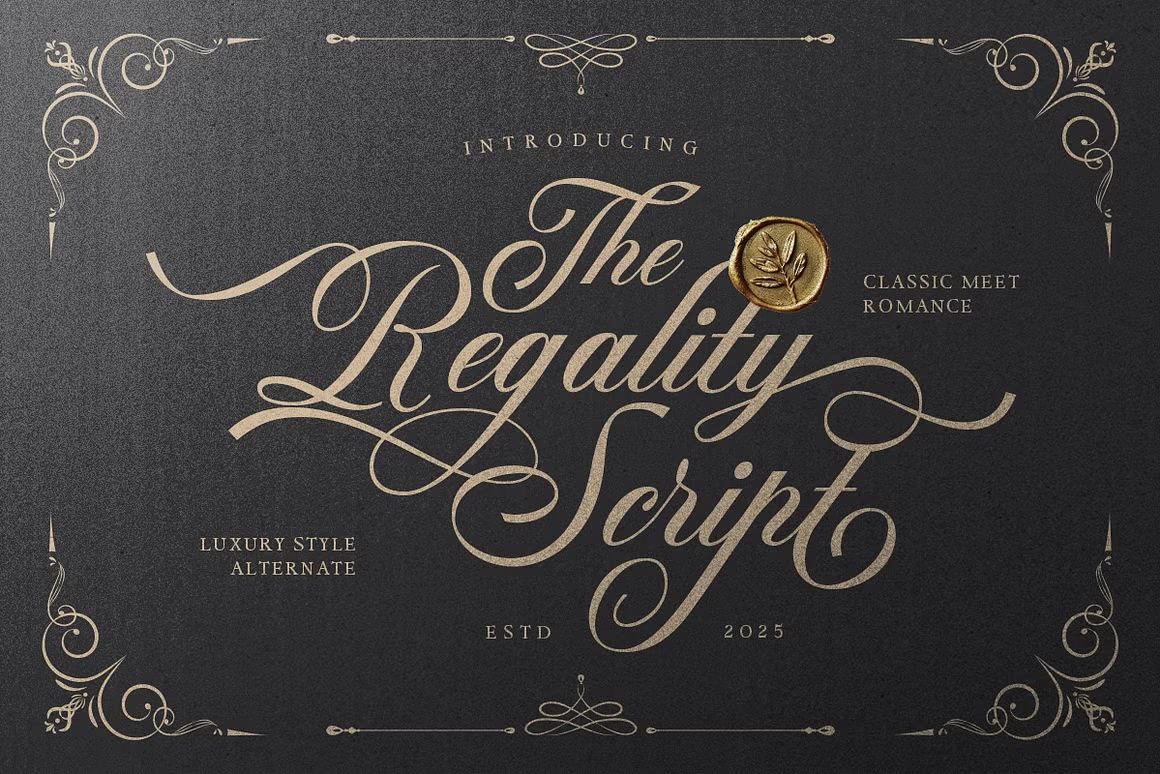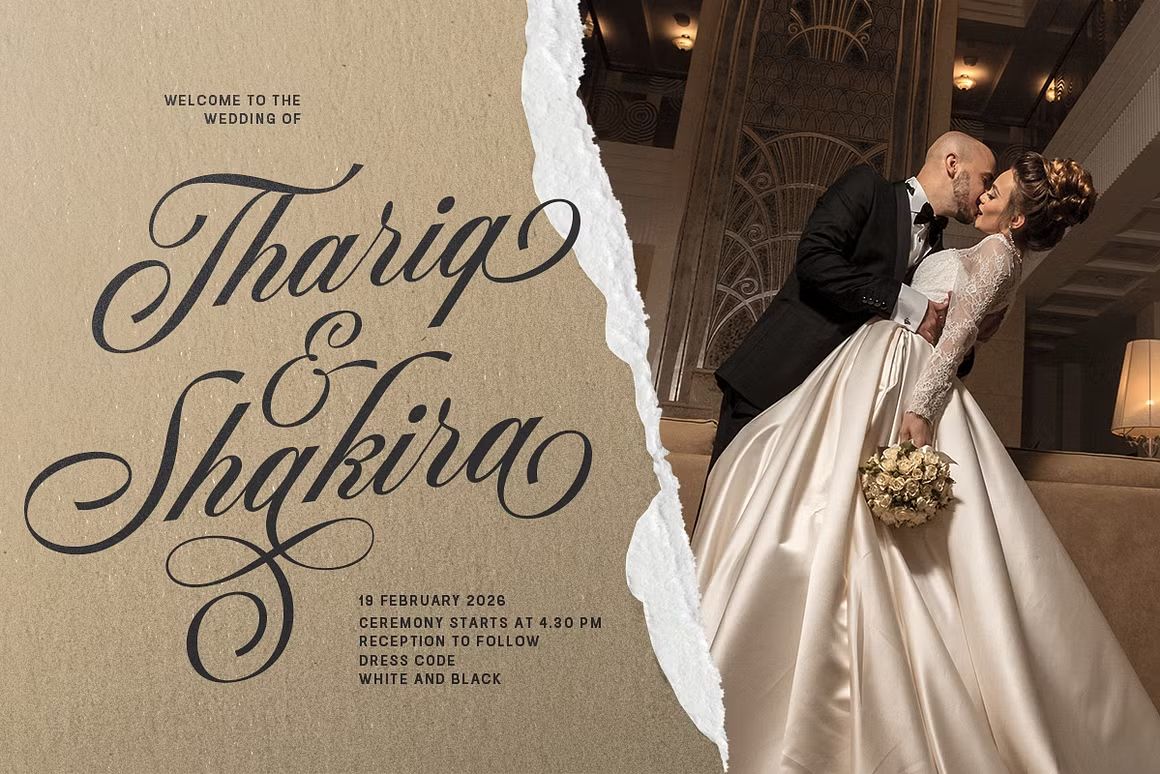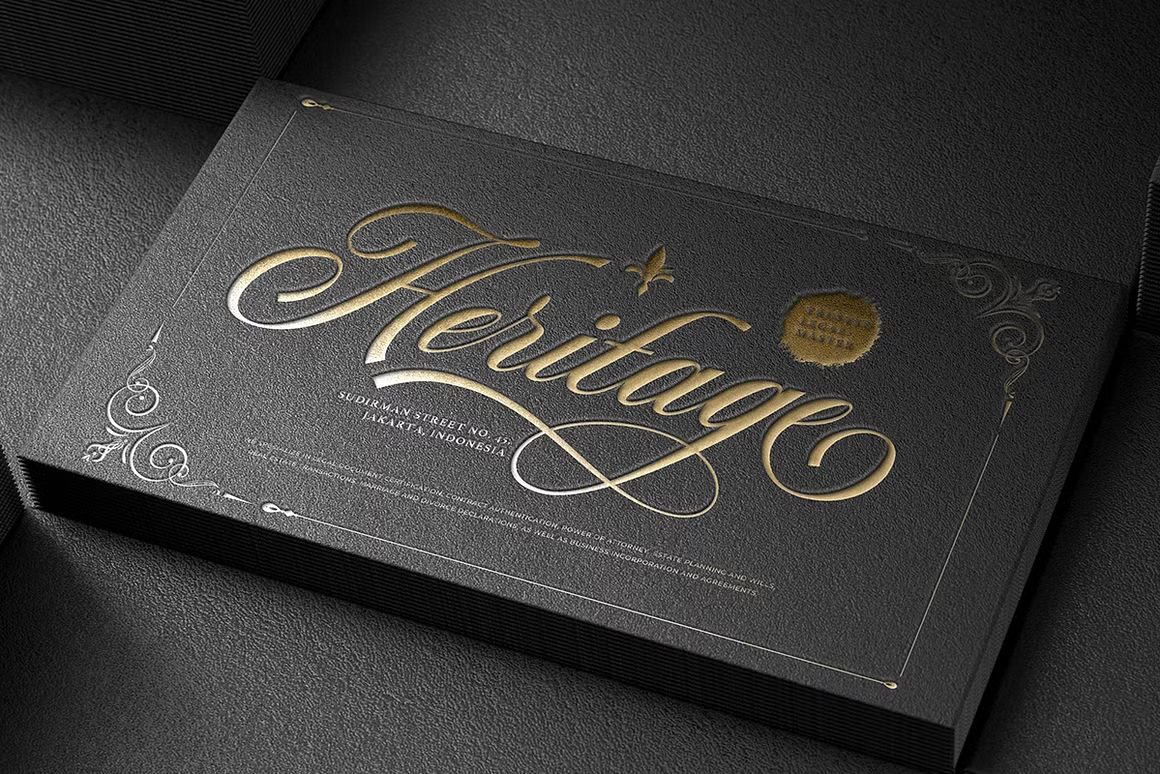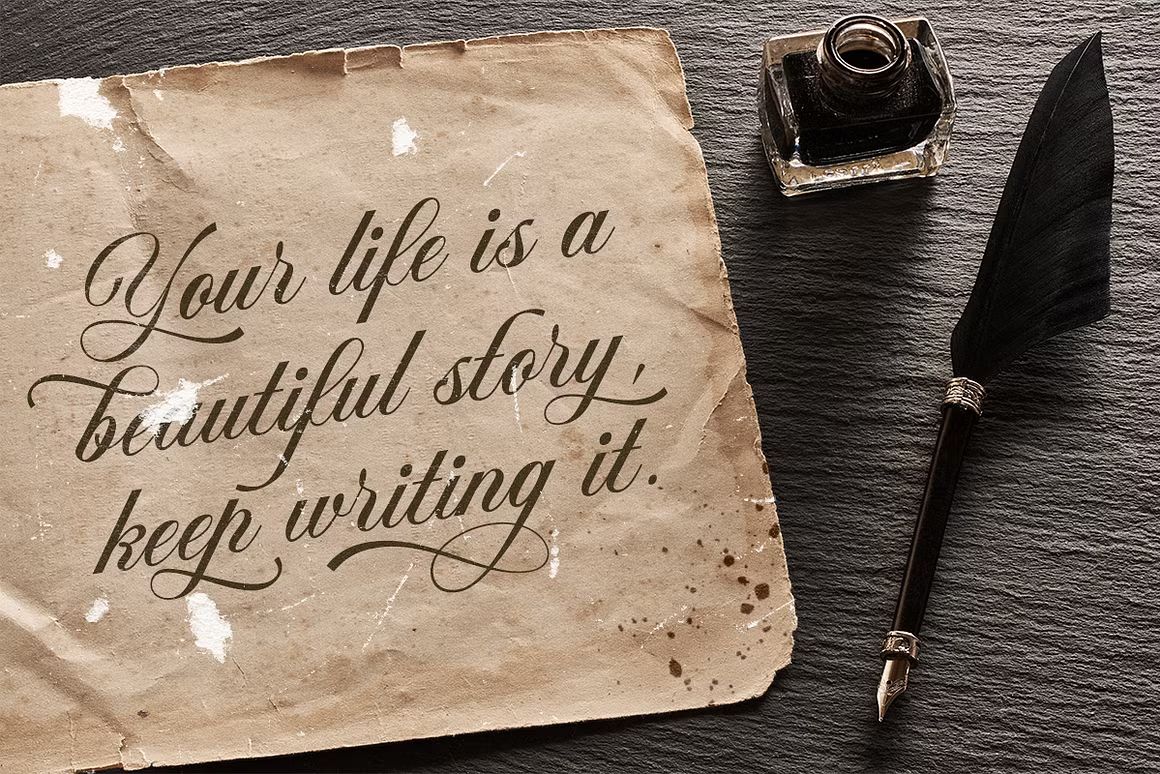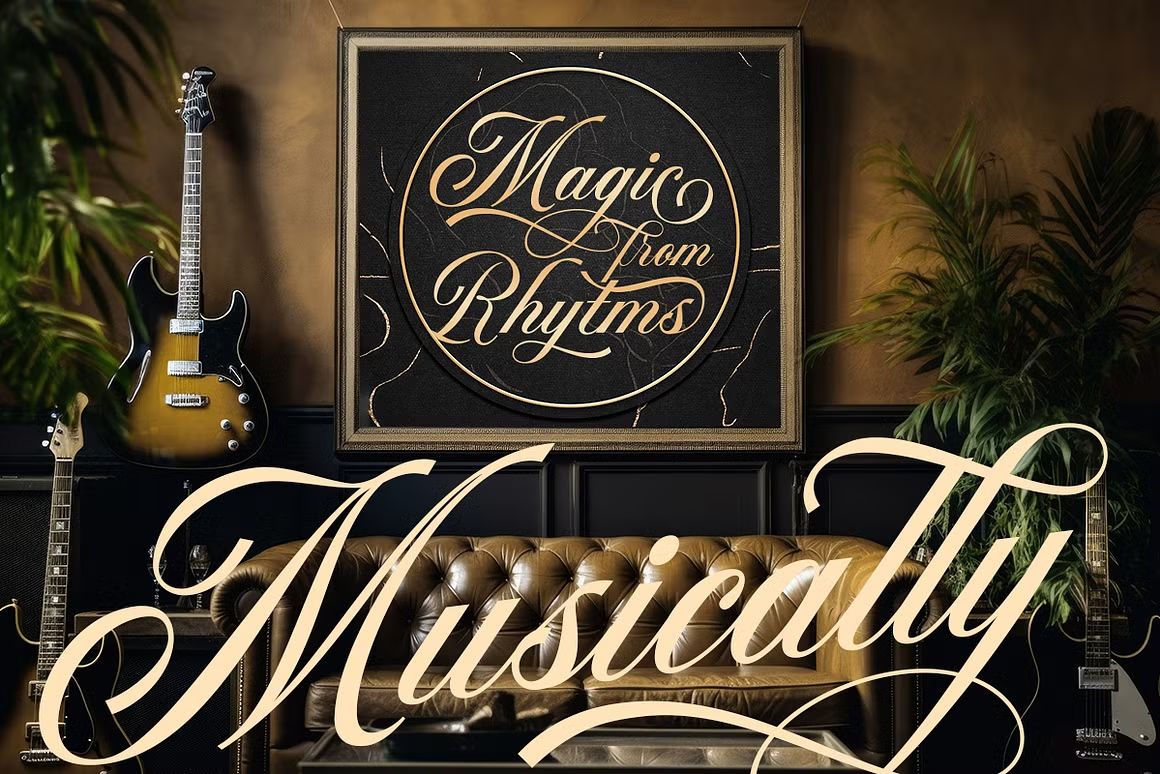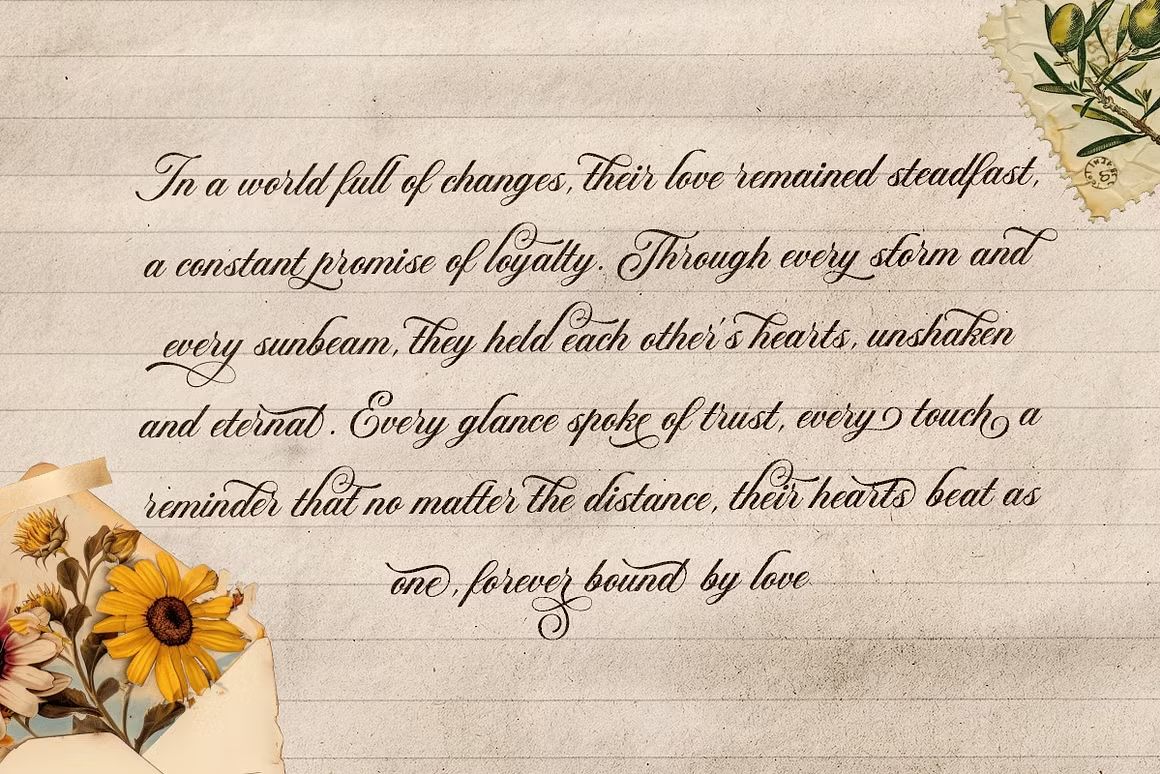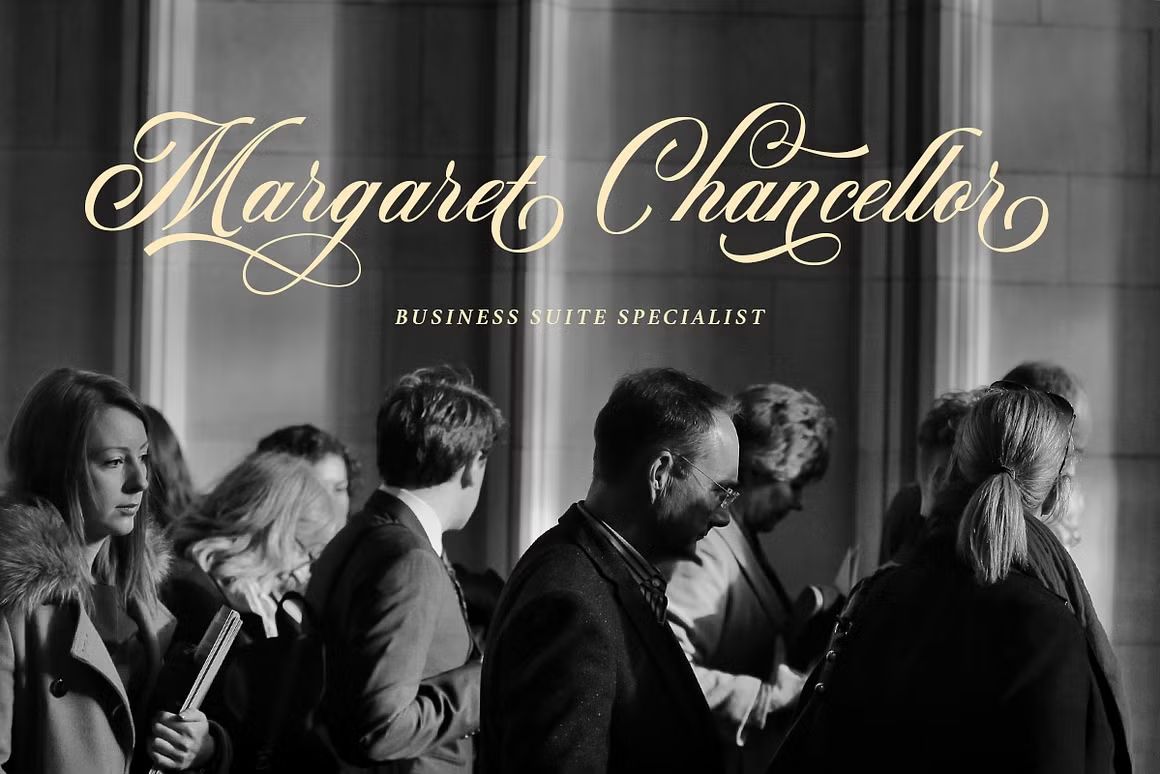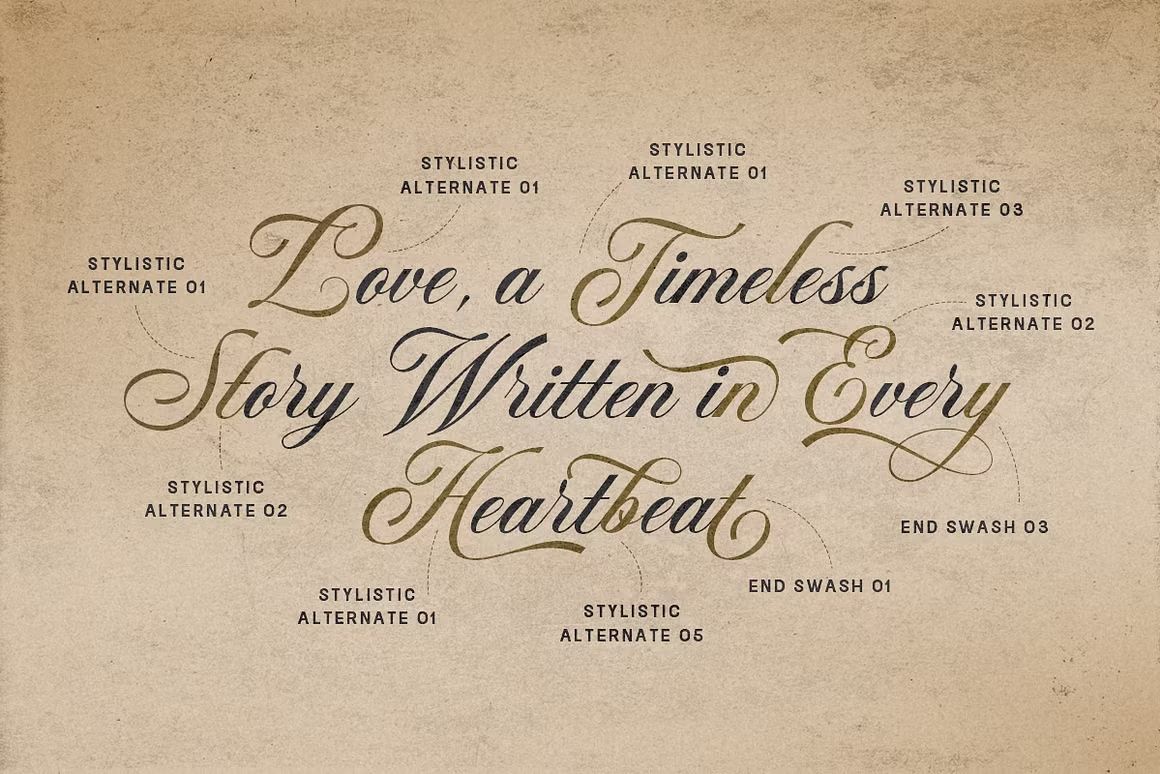
Regality – Script Font
Regality adalah font script elegan dengan sentuhan mewah dan garis tulisan tangan yang anggun. Didesain untuk memberikan kesan eksklusif dan feminin, Regality sangat cocok digunakan untuk undangan pernikahan, branding premium, logo mewah, kutipan estetik, dan kemasan produk elegan. Setiap huruf dirancang dengan detail halus untuk tampilan yang berkelas dan romantis.
• Script font dengan gaya mewah dan kaligrafi modern
• Ideal untuk wedding, branding premium, dan desain elegan
• Termasuk huruf besar, kecil, angka, simbol, dan ligatur